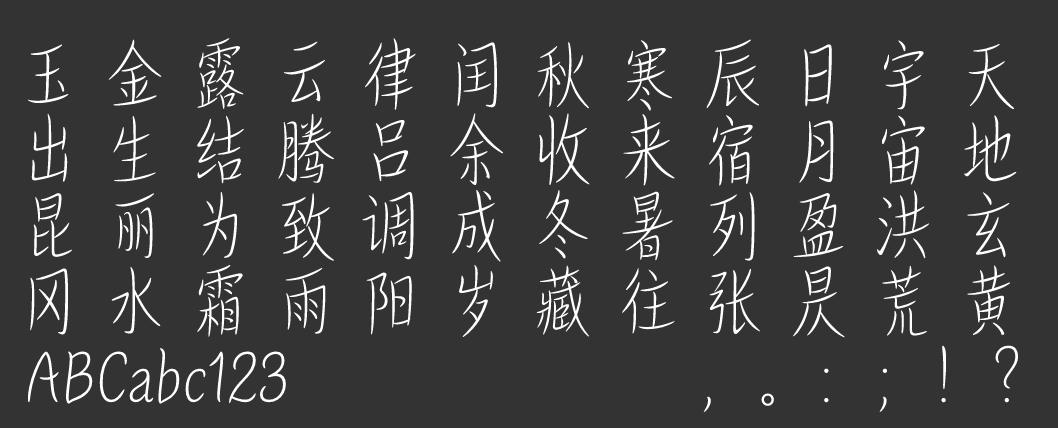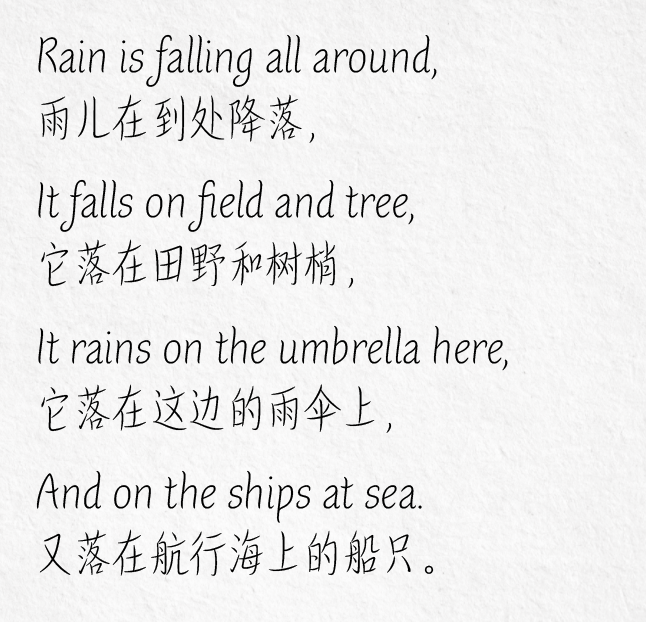
汉仪浅光|字体之星获奖作品
汉仪浅光是第二届字体之星正文组二等奖的获奖作品。它是一款清新自然,优雅灵动的字体。汉仪浅光是一款手写字体,笔画自然舒展轻盈,形似柳叶枝条,又好像一道道光线,给人舒适,休闲的感觉。
汉仪浅光|字形修长
汉仪浅光的字形修长,重心偏高,中宫舒展。让字体透露出了优雅、秀丽和高挑的文艺气质。
汉仪浅光的所有笔势均向右提收,体现了手写体的书写感。字形风格统一,犹如被微风吹拂着的柳叶般充满生机。
汉仪浅光|曲线细腻
汉仪浅光的笔画较细,点画灵动飘逸。字体简洁而不呆板,表现出字体独特的秀美气质。
汉仪浅光的笔画里没有直线,是以细腻生动的弧线组成。汉仪浅光的笔画结构布置均匀,带给人清雅、秀丽的视觉感受。
汉仪浅光|连笔生动
作为一款手写字体,汉仪浅光的连笔生动自然流畅,且相同的笔画在不同的字体结构中也有不同的连笔形态。
汉仪浅光|中西文匹配
汉仪浅光的西文字形同样修长,x字高较高,与中文字形结构相匹配。
西文字母的排版效果轻松舒适,与中文搭配起来十分和谐。
汉仪浅光|排版效果